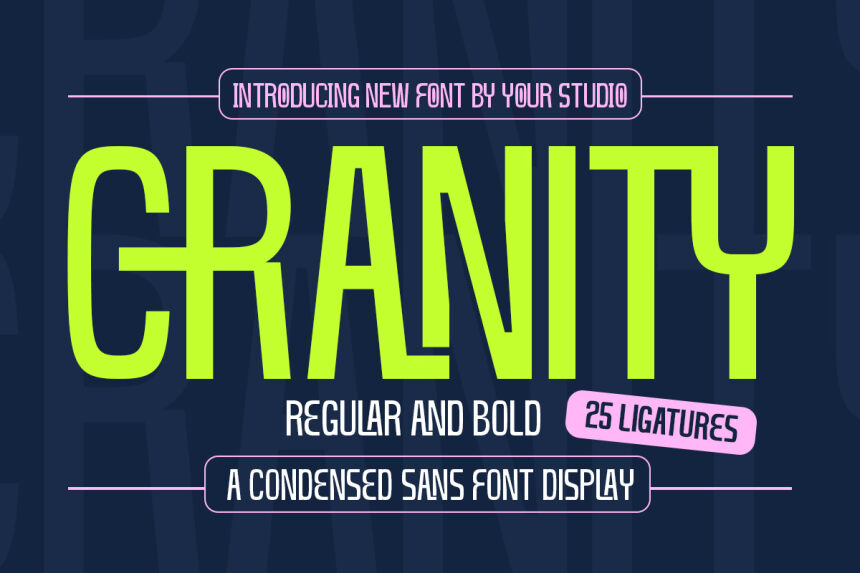
Cranity, de Afkari Studio, es una tipografía sans serif gratuita de estilo redondeado, con un aire suave y contemporáneo. Sus letras se sienten altas y minimalistas, con esquinas suaves, trazos equilibrados y una geometría sencilla que aporta calma en lugar de frialdad.
Esto convierte a esta fuente gratuita en una opción ideal para la identidad de aplicaciones, logotipos de startups, etiquetas de productos, titulares de pósteres y encabezados en redes sociales donde se busca modernidad sin bordes rígidos. También funciona muy bien en títulos cortos y subtítulos editoriales sobrios, ya que sus curvas generosas y su espaciado aireado dan a las palabras un ritmo sencillo y abierto.